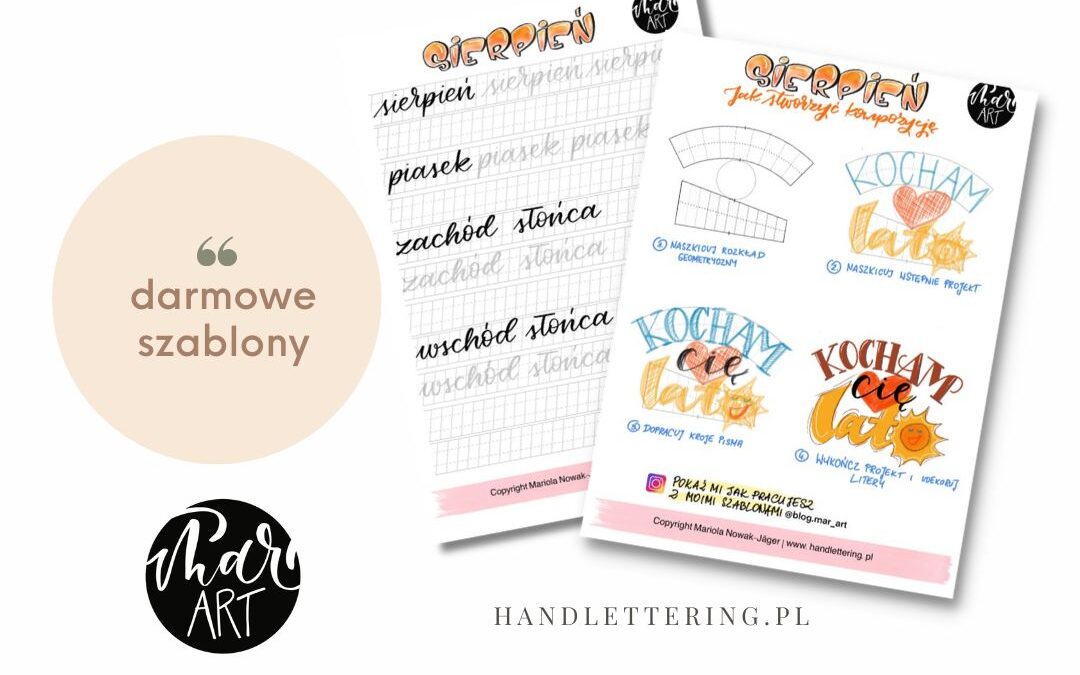
Połowa lata już z nami. Ciepłe słoneczne dni nie sprzyjają siedzeniu w domu. Ale być może masz troszkę czasu i chcesz wypróbować coś nowego. Przygotowałam dla Ciebie wakacyjny lettering w postaci instrukcji krok po kroku. Zapoznaj się z 4 prostymi krokami i wykonaj ze mną swoją pierwszą pracę.
Krok 1: Naszkicuj układ geometryczny
Policz ilość słów w sentencji, którą chcesz wykonać. Następnie naszkicuj proste figury geometryczne: jedna figura na jedno słowo. Możesz wykorzystać prostokąty, koła, trójkąty, cokolwiek Ci przyjdzie do głowy. Na samym początku umieszczaj figury geometryczne jedna pod drugą. Gdy Twoje kompozycje będą coraz bardziej złożone, możesz je umieszczać obok siebie lub zaplatać.
W większych figurach geometrycznych umieszczaj dłuższe słowa, a w mniejszych krótsze.
Krok 2: Naszkicuj wstępnie projekt
Teraz czas, aby umieścić pojedyncze słowa w figurach geometrycznych. W tym kroku nie musisz mieć sprecyzowanego planu na krój pisma. Posiłkuj się tutaj ołówkiem, testuj różne kroje i wybierz ten, który Ci się najbardziej podoba.
Krok 3: Dopracuj kroje pisma
Nadszedł czas, aby dopracować wybrane kroje pisma w kroku 2. Gdzie będą zawijasy, a gdzie szeryfy. Eksperymentuj. Pogrub może niektóre litery. Pracuj nadal ołówkiem.
Krok 4: Wykończ projekt i udekoruj litery
Nadszedł czas na flamastry, brush peny lub kredki. Zanim jednak zaczniesz kolorować i wypełniać litery- wymaż lekko ołówek, aby nie przebijał od spodu. Zastanów się też nad kolorem liter. Jaki kolor kojarzy Ci się z danym słowem. Dla mnie wybór był jasny:
- kocham – czerwony
- cię w sercu- jasne, że czerowny
- lato, a w nim słońce- zółty
Na sam koniec nanieś białe akcenty, tzw. highlight-ty oraz obrysy lub cienie na litery.